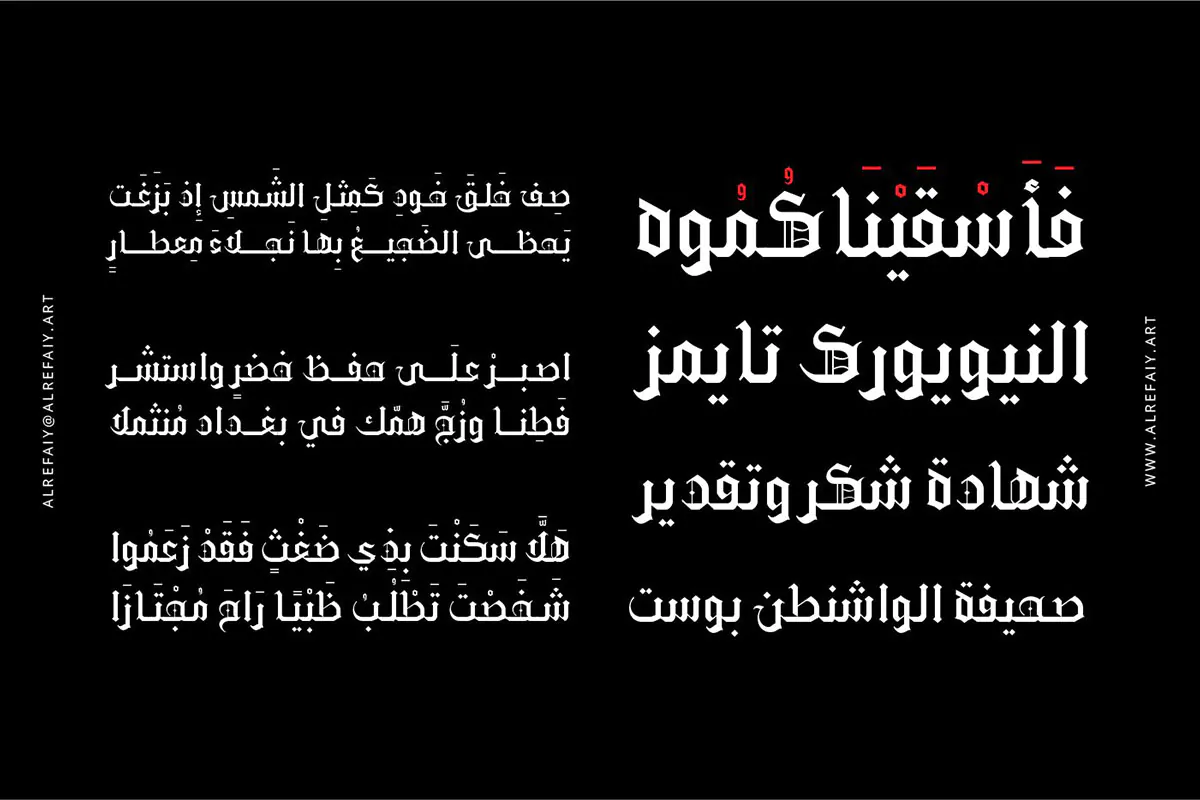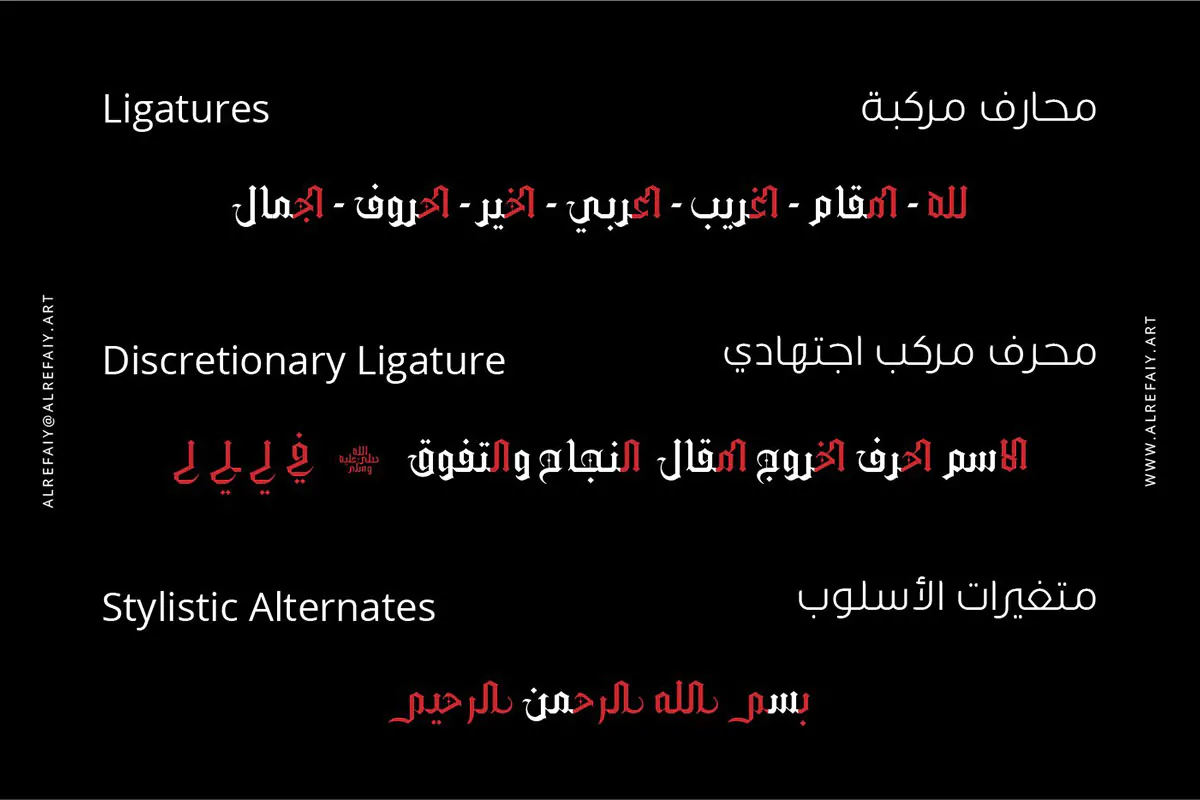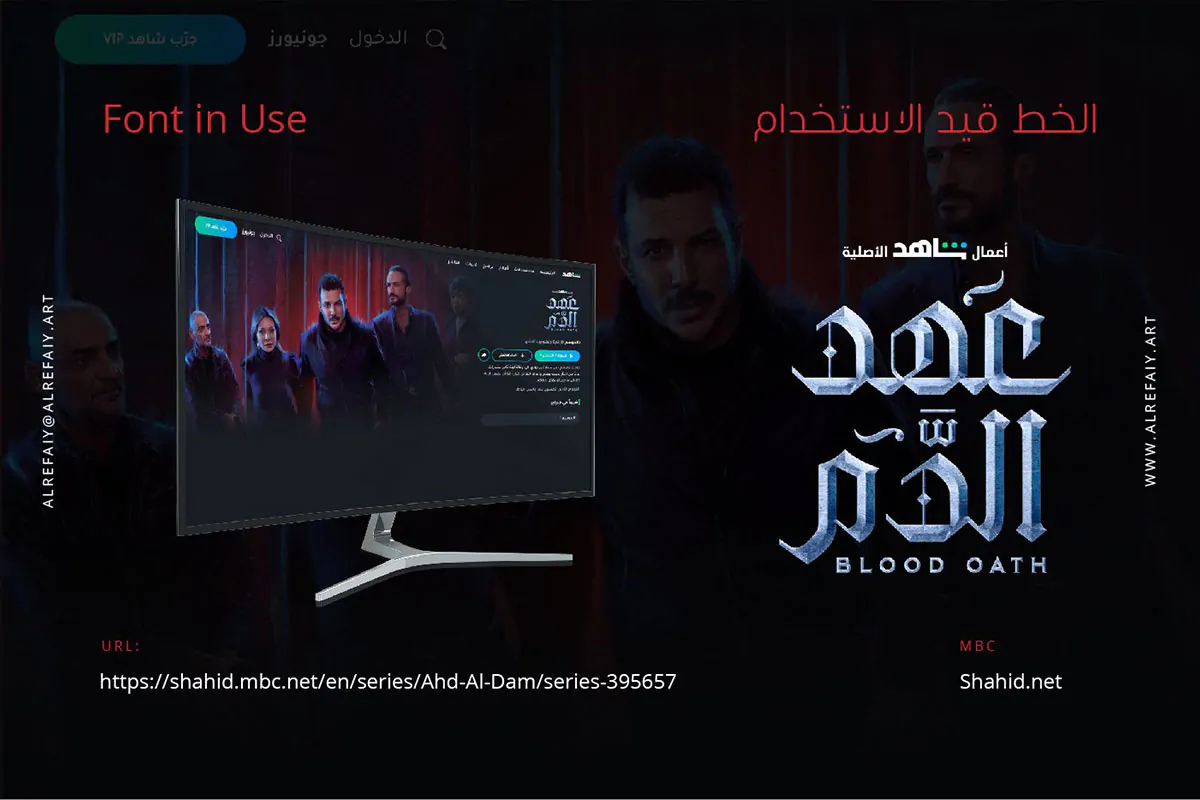
فونت فارسی حماسی و قرون وسطی گوتیک Gothic
فونت فارسی حماسی و قرون وسطی گوتیک
فونت فارسی حماسی و قرون وسطی گوتیک Gothic یک قلم بلک لتر فارسی، عربی، اردو و انگلیسی فوق العاده زیبا است که مناسب برای استفاده در طراحی انواع پوستر، بنر، تیتراژ فیلم و سریال، کارت ویزیت، بسته بندی محصولات و … میباشد.